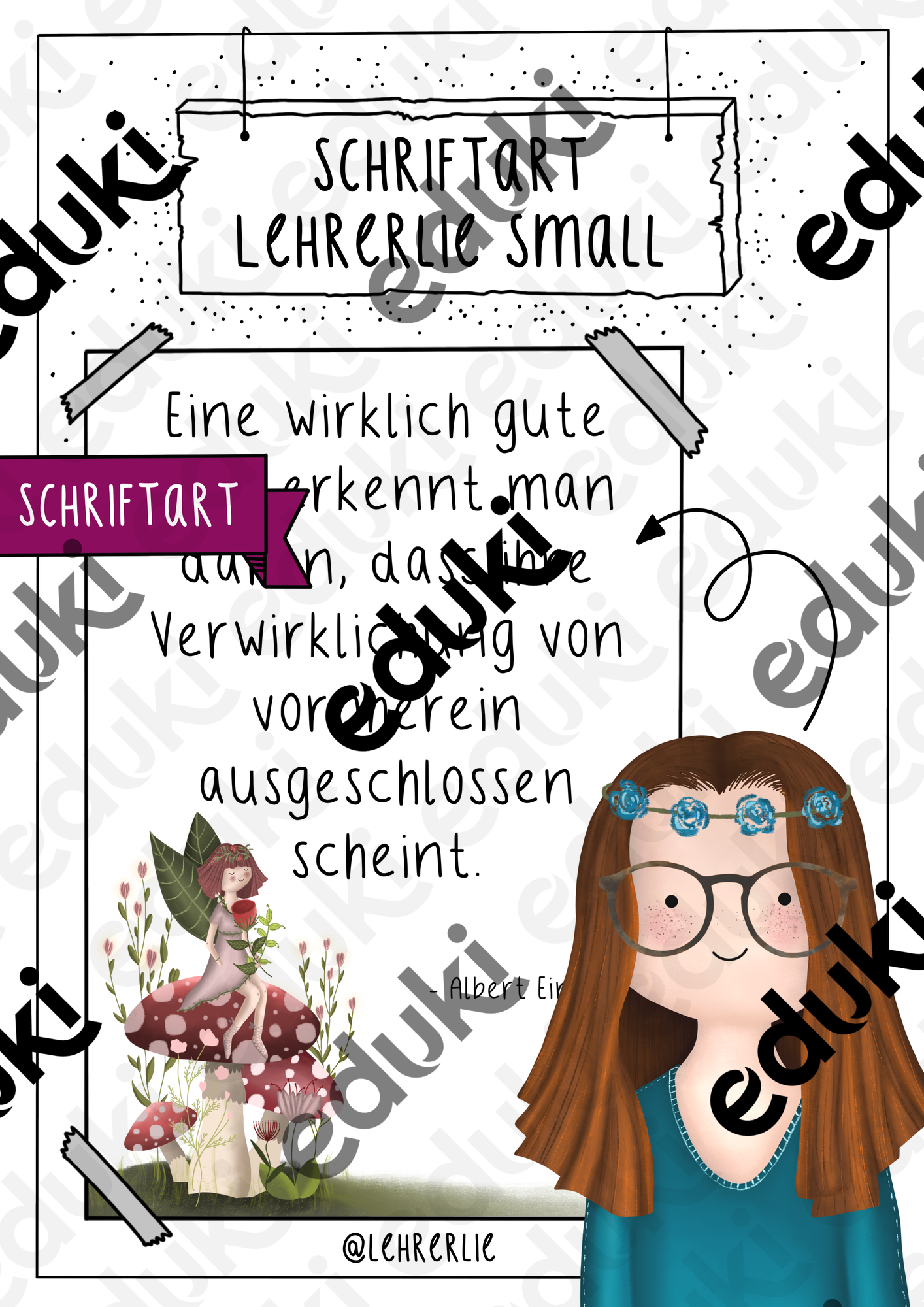
Schriftart / Handschrift
Lehrerlie small - Schriftart
Die Schriftart ist einfach unglaublich toll. Sie ist gut leserlich und sieht auf den Arbeitsblättern echt toll aus!